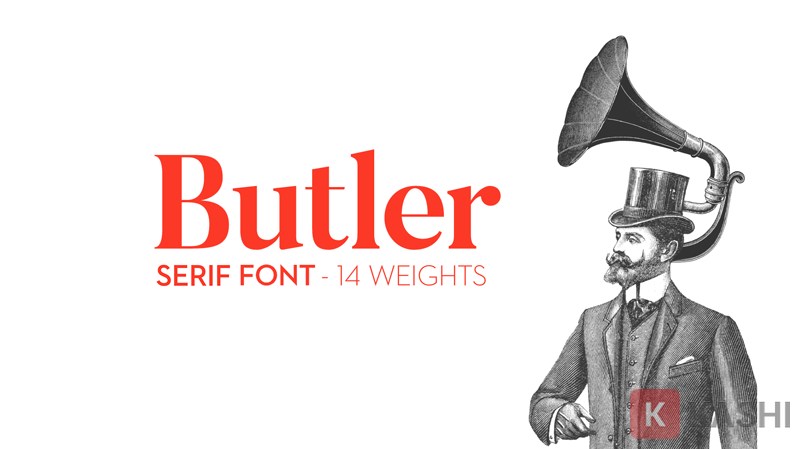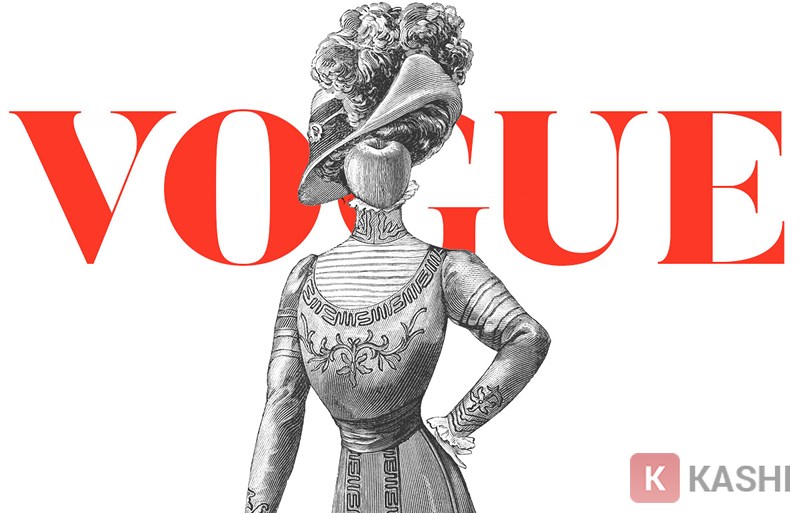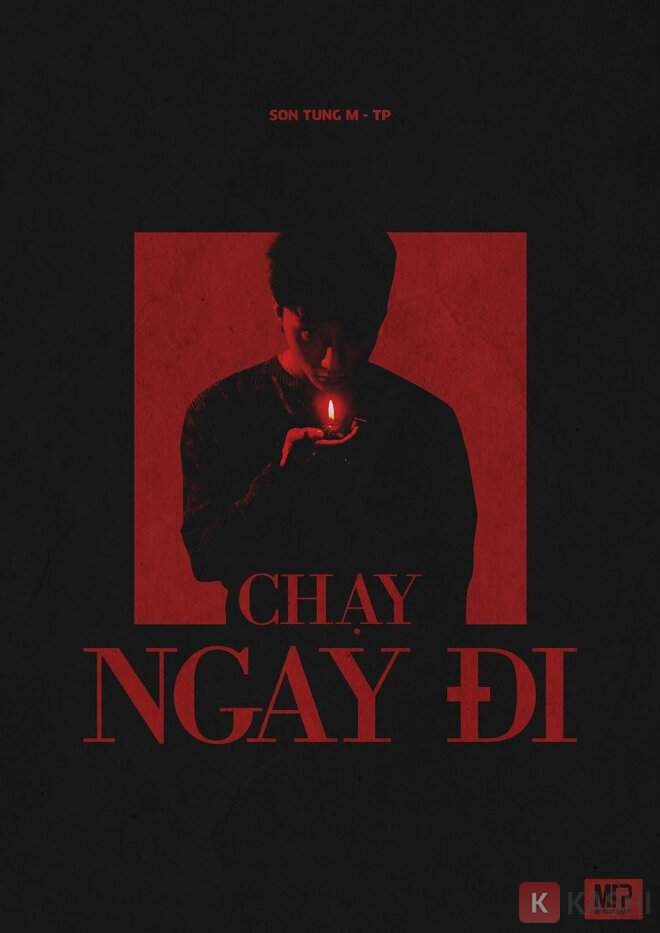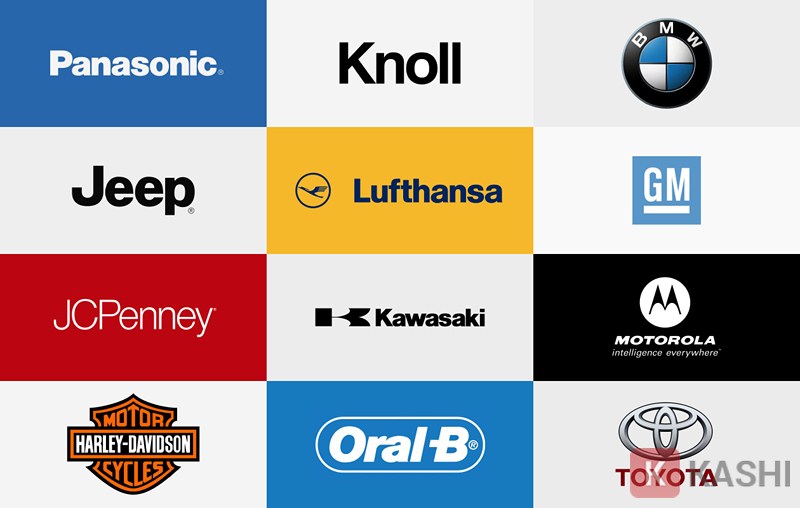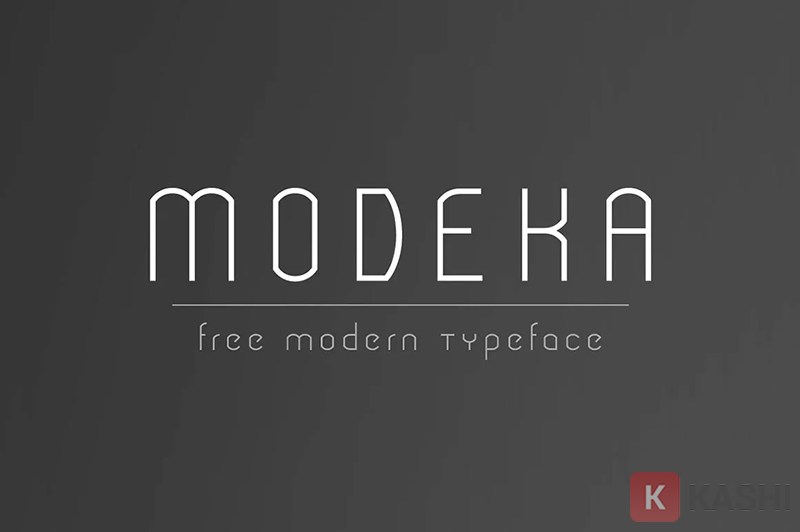
Top 10+ Font Chữ Kiến Trúc Đẹp và Ấn Tượng Nhất 2025
Bạn đang tìm kiếm font chữ phù hợp cho thiết kế kiến trúc? Bạn muốn bản vẽ của mình trở nên nổi bật và thu hút hơn? Bài viết này sẽ giới thiệu đến bạn top 10+ font chữ kiến trúc đẹp, ấn tượng và được ưa chuộng nhất hiện nay, cùng với link tải miễn phí để bạn sử dụng ngay.
Font chữ đóng vai trò quan trọng trong thiết kế đồ họa kiến trúc, tạo nên sắc thái riêng cho bảng biểu, bản vẽ kỹ thuật và mô hình. Lựa chọn font chữ phù hợp giúp bản vẽ trở nên logic, thu hút và chuyên nghiệp hơn.
Font Chữ Kiến Trúc là gì?
Font chữ kiến trúc là yếu tố cốt lõi trong thiết kế đồ họa, đặc biệt là trong lĩnh vực kiến trúc. Chúng được sử dụng để tạo ra các bảng biểu, bản vẽ kỹ thuật và mô hình, mang lại nét đặc trưng riêng cho từng dự án. Việc lựa chọn font chữ chính xác giúp truyền tải thông tin một cách rõ ràng, tạo sự logic cho bản vẽ, dù là vẽ tay hay sơ đồ, kết nối giữa ý tưởng và hiện thực.
Top 10+ Font Chữ Kiến Trúc Việt Hóa, Viết Tay Đẹp Nhất 2025
Dưới đây là danh sách các font chữ kiến trúc đẹp và ấn tượng, kèm theo link tải miễn phí:
1. Font Futura
Được tạo ra bởi Paul Renner vào năm 1928, Futura là một biểu tượng của thiết kế đồ họa hiện đại. Lấy cảm hứng từ trường phái Bauhaus, Futura sử dụng sự kết hợp hài hòa giữa các đường thẳng và đường cong, tạo nên sự cân bằng cho văn bản. Font chữ này thường được sử dụng cho các văn bản ngắn gọn trong bảng kiến trúc, như tiêu đề và phụ đề, hoặc để nhận diện hình ảnh trong các tòa nhà.
2. Font Gotham
Gotham, được thiết kế bởi Tobias Frere Jones, lấy cảm hứng từ chữ cái trên biển báo công cộng kết hợp với màu sắc kiến trúc. Font chữ này được sử dụng rộng rãi trong cộng đồng thiết kế, đặc biệt là trong danh thiếp và logo, tạo ấn tượng mạnh mẽ cho người xem.
Font chữ Gotham
3. Butler
Butler là sự kết hợp giữa font Bodoni và Dala Floda, mang nét cổ điển phương Tây của thế kỷ XVII, XVIII. Font chữ này rất phù hợp với các thiết kế kiến trúc mang phong cách thanh lịch, quý phái. Đặc biệt, Butler thường là font chữ mặc định trong nhiều phần mềm đồ họa.
Kiểu chữ Butler Kiểu chữ ButlerButler script- font chữ thiết kế
4. Bodoni
Được tạo ra vào năm 1767 bởi Giambattista Bodoni, Bodoni mang tính thẩm mỹ cao và vượt thời gian. Với tập hợp các đường nét đặc trưng, Bodoni thường được sử dụng cho các điểm nhấn như tiêu đề và chi tiết trong bản vẽ kiến trúc.
Kiểu chữ Bodoni
5. Helvetica
Helvetica là lựa chọn phổ biến của nhiều kiến trúc sư nhờ sự tối giản và các đường thẳng đặc trưng. Được thiết kế vào thế kỷ XX bởi Max Miedinger và Eduard Hoffmann, Helvetica gắn liền với thiết kế đồ họa hiện đại, mang đến sự trung tính và súc tích.
Các thương hiệu nổi tiếng sử dụng font Helvetica
6. Modeka
Modeka là font chữ linh hoạt và tinh tế, lý tưởng cho việc soạn thảo bảng biểu. Sự kết hợp hài hòa giữa các đường thẳng và đường cong tạo nên nét độc đáo cho font chữ này. Modeka thường được sử dụng cho tiêu đề, phụ đề và chi tiết văn bản trong bảng vẽ kiến trúc.
Font chữ kiến trúc Modeka
7. Poplar
Được thiết kế bởi Barbara Lind và là một phần của Adobe, Poplar mang đến sự mạnh mẽ và cá tính cho thiết kế. Font chữ này phù hợp với nhiều ứng dụng, từ bảng biểu đến sơ đồ, và thường được sử dụng cho tiêu đề, phụ đề và chi tiết.
Mẫu chữ Poplar
8. Bauhaus
Được phát triển bởi Herbert Bayer vào năm 1925, Bauhaus mang tính vượt thời gian và vẫn được sử dụng rộng rãi cho đến ngày nay. Font chữ này thường được dùng cho tiêu đề và phụ đề trong bảng vẽ kiến trúc.